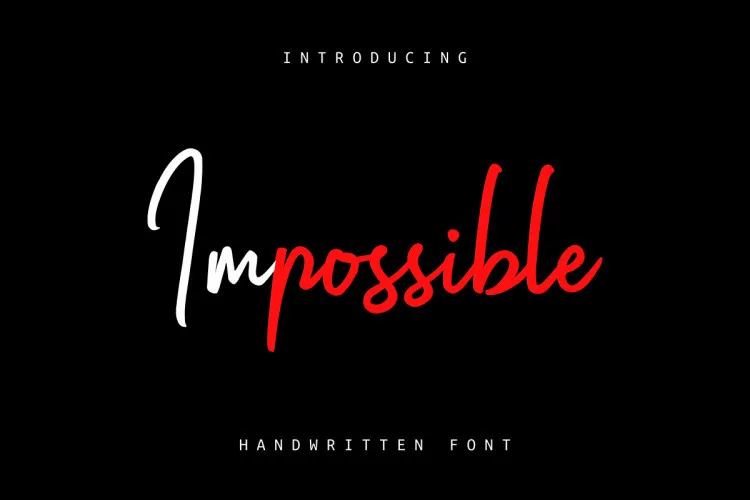
Impossible Script Font – Download Grátis
Descubra uma nova opção para seus projetos de design com a “Impossible Script Font”. Esta fonte de script é elaborada em estilo escrevado à mão, oferecendo um toque elegante e único que transforma qualquer projeto em algo autêntico e profissional. Desenvolvida pelo Ghuroba Studio, essa fonte moderna é leve e encantadora, com incrível personalidade própria. Seja para logotipos e identidades de marca, fotografias, convites ou até mesmo para embalagens, a “Impossible Script Font” oferece uma versão regular e itálica do estilo à mão. Esta fonte perfeita é ideal para adicionar um toque autêntico à sua arte digital, transformando as obras em algo que fala diretamente ao seu público. Experimente essa opção única e singular; pode revolucionar a forma como você trabalha com fontes de script.